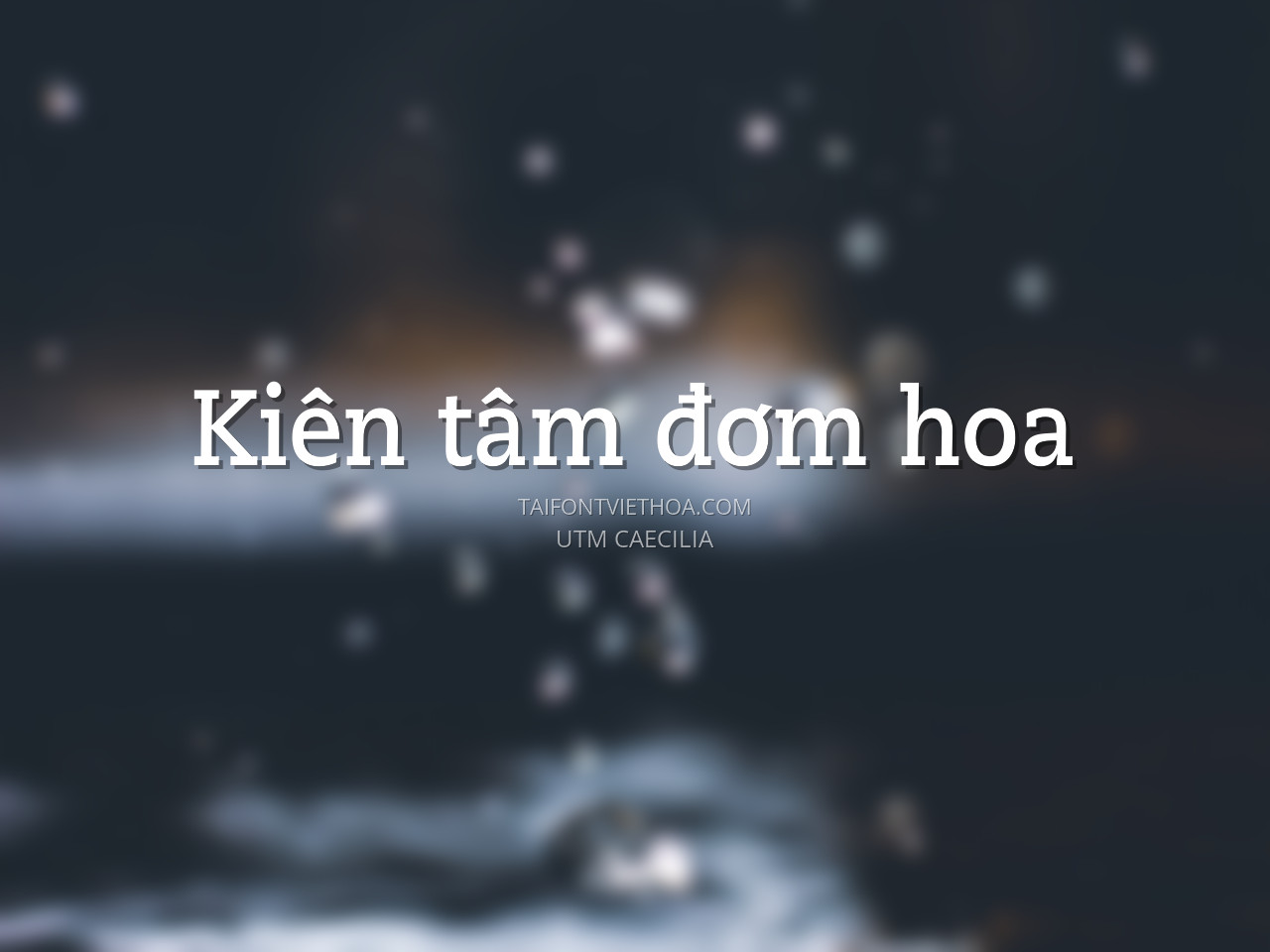
Font việt hóa UTM Caecilia KT
Giới thiệu về font UTM Caecilia KT
UTM Caecilia KT là phiên bản Việt hóa của font Caecilia – một kiểu chữ slab serif hiện đại và linh hoạt, được thiết kế bởi nhà thiết kế Peter Matthias Noordzij. Font gốc nổi bật với các nét chữ dày, vuông vức và chân chữ đặc trưng, tạo nên sự chắc chắn và cá tính. Phiên bản Việt hóa đã được hoàn thiện để hỗ trợ đầy đủ tiếng Việt cùng hơn 200 ngôn ngữ khác, giúp mở rộng khả năng ứng dụng trong nhiều dự án thiết kế đa dạng.
Đặc điểm thiết kế và ứng dụng của UTM Caecilia KT
UTM Caecilia KT sở hữu cấu trúc slab serif với các nét chữ dày, vuông vức và chân chữ nổi bật. Font có thiết kế chắc chắn, dễ đọc và rất phù hợp để tạo điểm nhấn trong các tiêu đề, logo và bảng hiệu. Font còn được trang bị nhiều ligature và glyph thay thế giúp tăng tính linh hoạt trong thiết kế.
Font thích hợp sử dụng trong các dự án thiết kế logo, nhận diện thương hiệu, quảng cáo, bảng hiệu, poster và các ấn phẩm truyền thông đa phương tiện. Các ngành nghề phù hợp gồm: quảng cáo, thời trang, công nghệ, sự kiện và truyền thông sáng tạo.
Thiết kế: Dalton Maag Ltd
Thiết kế: Mack Trinh Và Harry Dinh